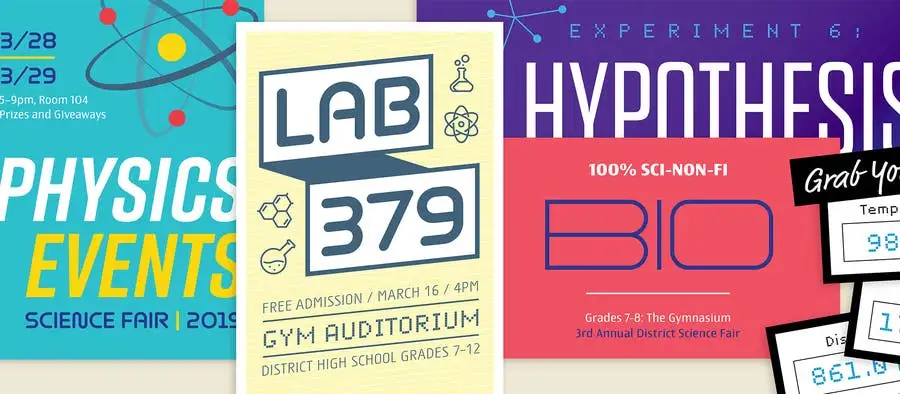
포토샵에서 글꼴 작업 시 반드시 고려해야 할 5가지 사항
어떤 글꼴을 디자인에 활용할지 결정하는 것이 그렇게 중요하게 생각되지 않을지 모르지만, 프로젝트의 흥망을 결정할 정도로 디자인에서 중요한 요소이죠. 프로젝트에 완벽히 어울리는 글꼴을 선택하는 다섯 가지 핵심 요소를 알아보겠습니다.
1. 감정
글꼴은 저마다 고유한 개성이 있습니다. 조용하거나 요란한 글꼴, 우스꽝스럽거나 진지한 글꼴이 있는가 하면, 글꼴을 통해 환상적인 미래를 묘사하거나 품위 있는 전통 디자인을 표현할 수도 있습니다. 프로젝트의 컨셉과 테마는 어떤 글꼴을 선택하는지에 따라 완전히 달라집니다.
글꼴은 다양한 감정을 전달할 수 있습니다. 이 파티 초대장에 사용된 가볍고 신나는 모양의 글꼴은 즐거운 파티 분위기를 표현해줍니다. 이미지 출처: 나탈리 로드리게즈(Nathalie Rodriguez)
2. 가독성
아무리 멋진 글꼴이라도 읽을 수 없다면 무슨 소용이 있을까요? 오늘날 글꼴에 대한 디자이너의 요구는 점점 까다로워지고 있습니다. 작은 스마트워치 화면과 대형 광고판을 비롯한 모든 오프라인, 디지털 디스플레이 환경에서 글꼴은 효과적으로 내용을 전달해야 합니다. 해당 글꼴이 다양한 크기와 구성에 잘 어울리는지, 빠르게 인식되고 쉽게 읽히는지 확인해야 하죠.
모든 디지털과 오프라인 플랫폼에서 가독성이 뛰어난 글꼴을 선택해야 합니다. 읽기 어려운 글꼴은 메시지를 효과적으로 전달할 수 없기 때문입니다. 이미지 출처: 릴리 아이 산트곤(Lily I Santgon)
3. 변별성
글꼴은 실용성은 물론, 창의성도 겸비해야 합니다. 모든 디자인은 시선을 사로잡기 위해 경쟁하죠. 특히 독특하면서도 치밀하게 구성된 글꼴 시스템은 경쟁사와의 차별화를 위한 완벽한 브랜드 전략입니다.
벨로 바이킹(Velo Viking)의 독특한 글꼴은 덴마크풍의 친근한 이미지로 브랜드 아이덴티티를 강화했습니다. 이미지 출처: 마르텐 데커스(Maarten Deckers)
4. 유연성
글꼴은 시간의 흐름과 함께 확장 및 업데이트되는 유연한 디자인 요소입니다. 그러므로 다른 글꼴, 색상 및 스타일과 잘 어울리는 글꼴을 선택해야 하죠. 그래야 새로 추가된 디자인 요소와 일관성을 유지하며 프로젝트를 넓혀나갈 수 있습니다.
스쿠프 앤 콘즈 아이스크림 컴퍼니(Scoop & Cones Ice Cream Company)의 브랜딩 및 패키징 디자인 프로젝트에 사용된 글꼴은 각자 고유한 스타일이 있지만 다른 글꼴과도 조화롭게 어우러집니다. 이미지 출처: 마르카 네트워크(Marka Network)
5. 안정성
모든 플랫폼에서 프로젝트를 공유하고 모션과 같은 요소를 적용할 때는 안정적인 글꼴을 사용해야 합니다. 이미지 출처: 아르티코 에스튜디오(Artico Estudio)